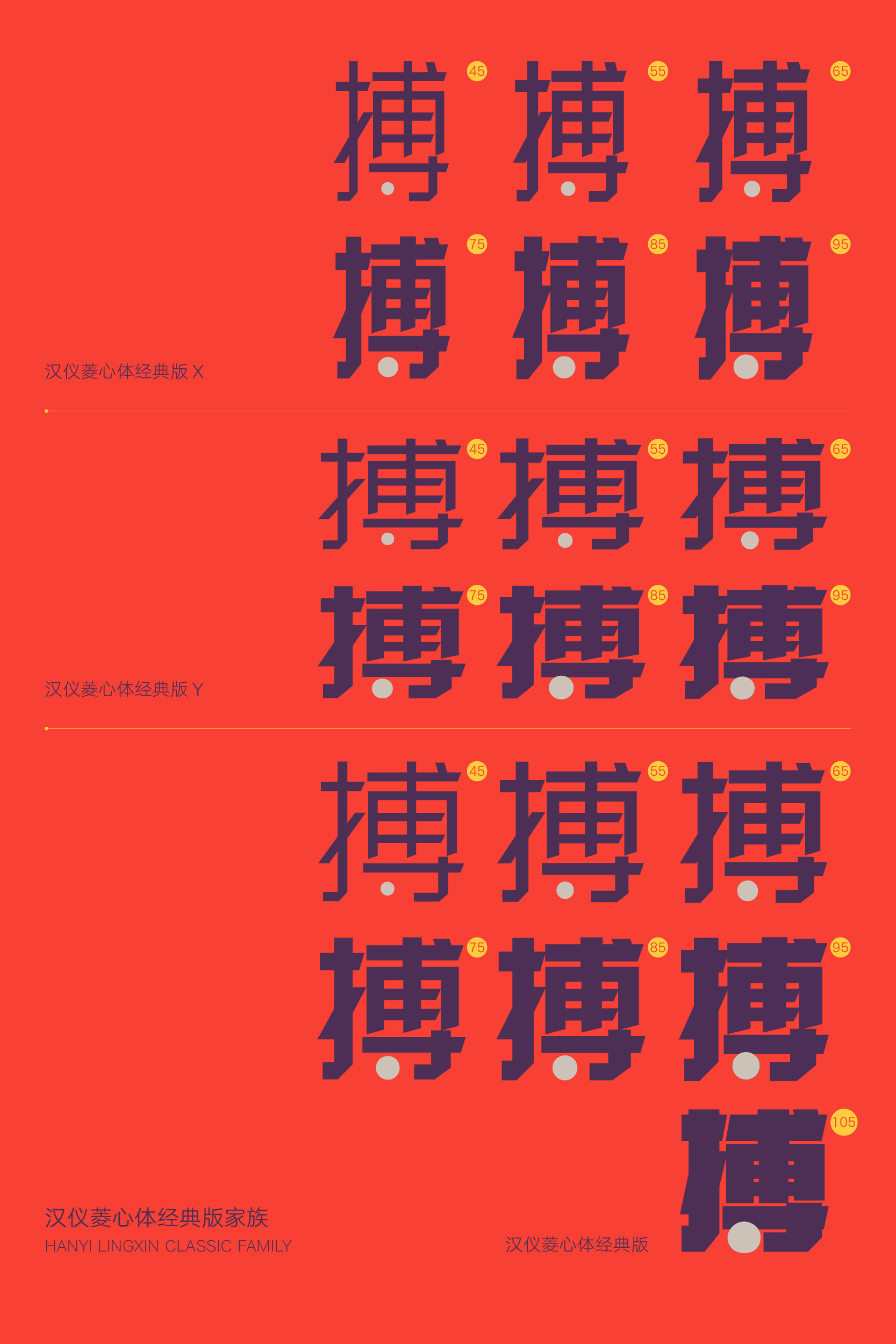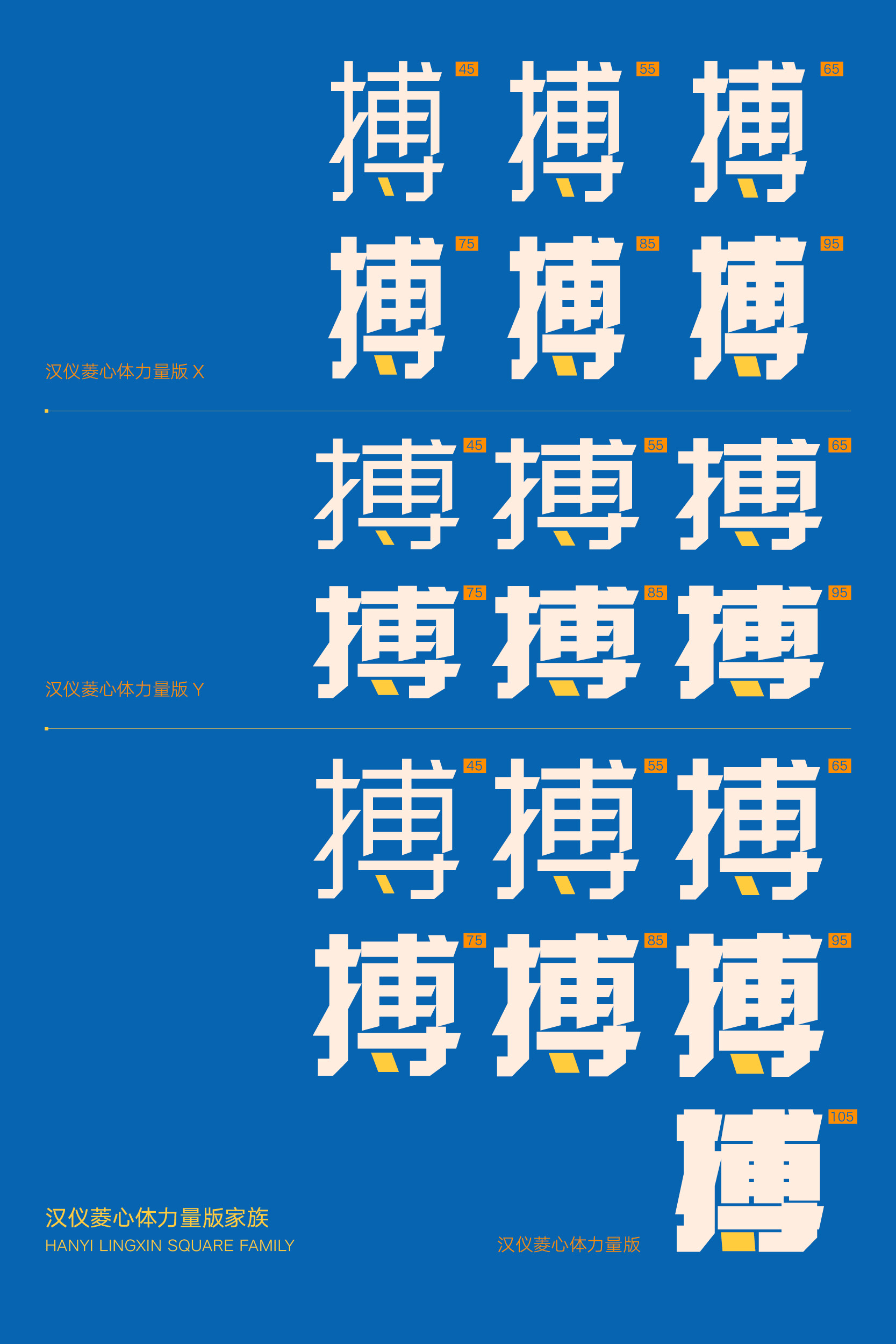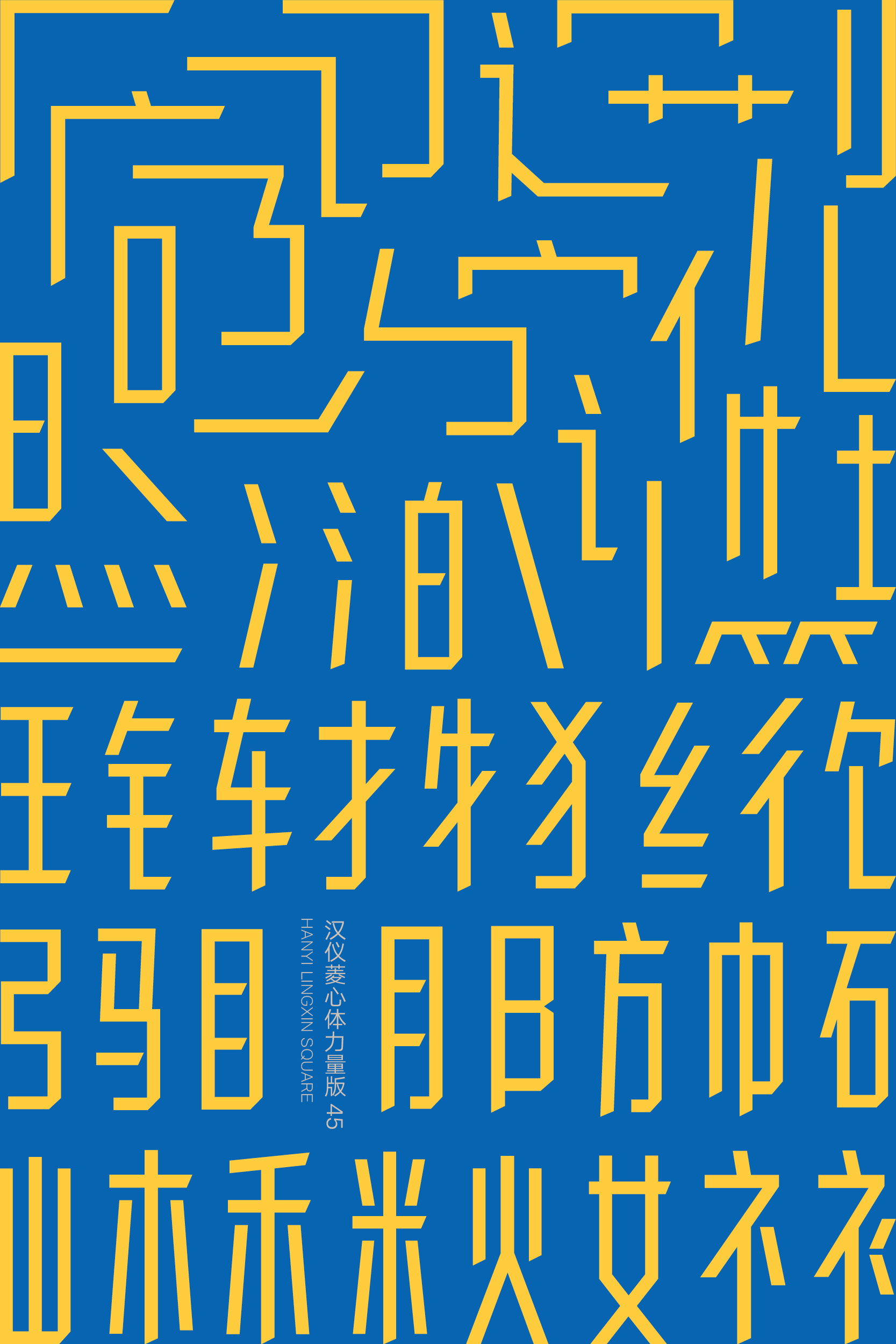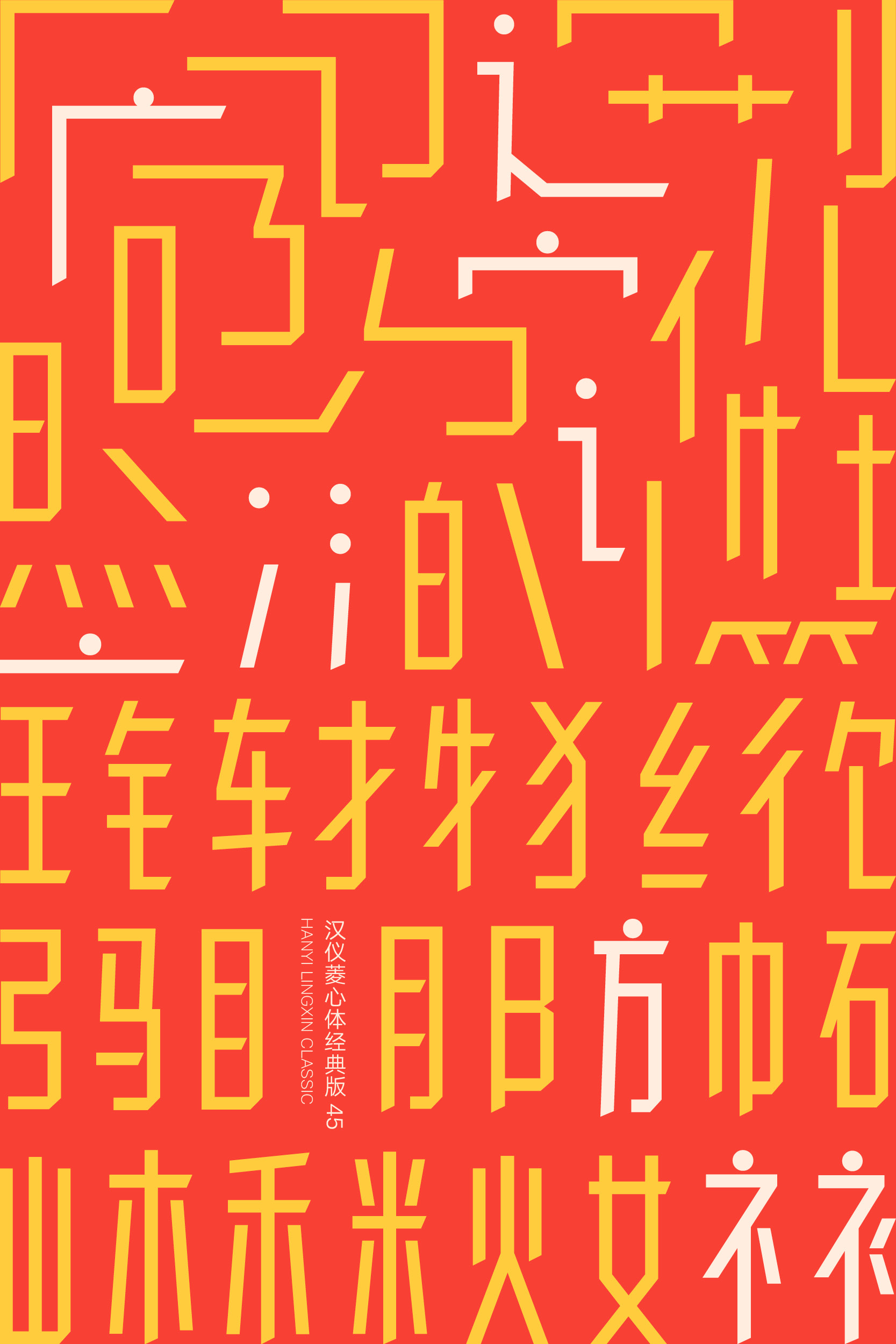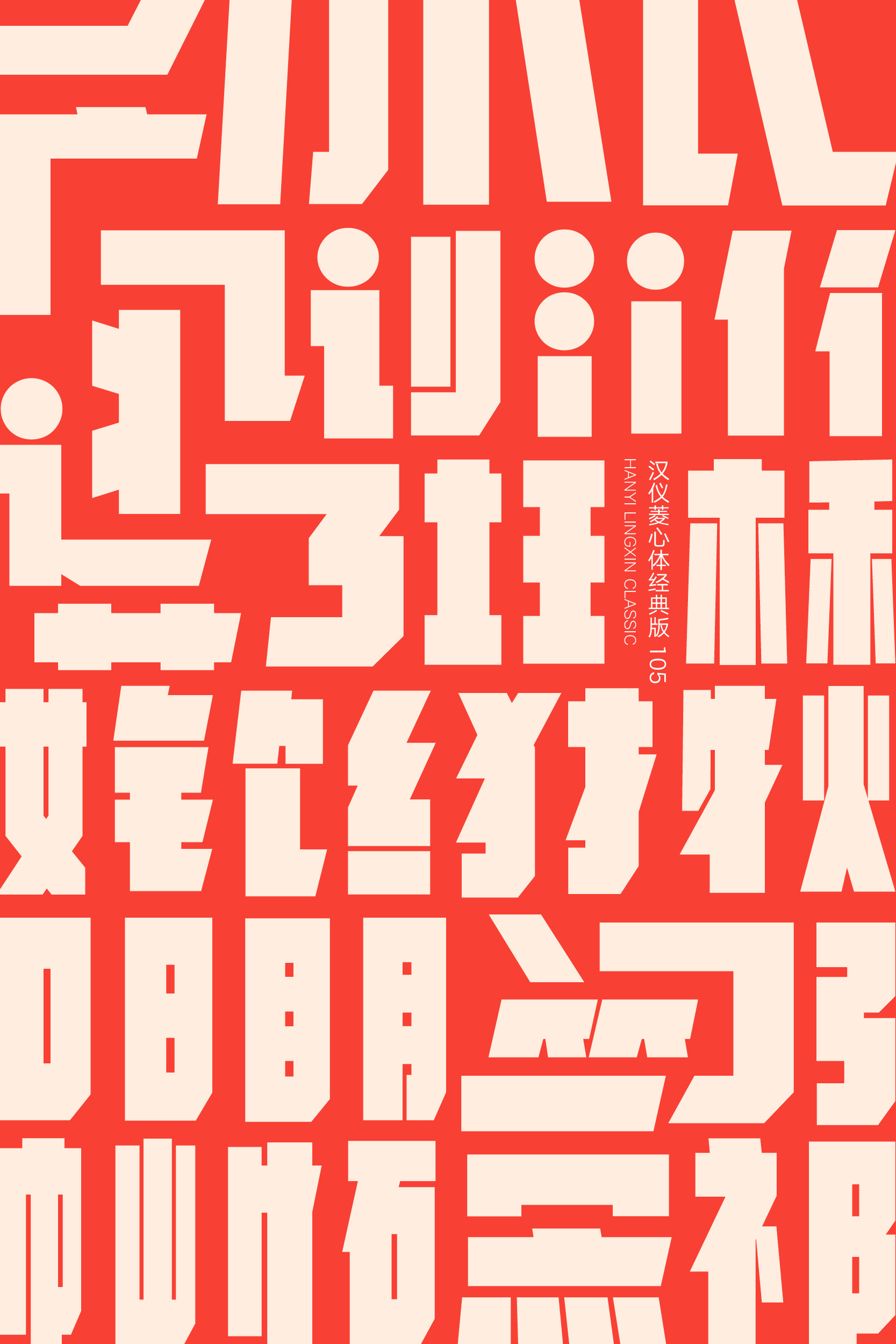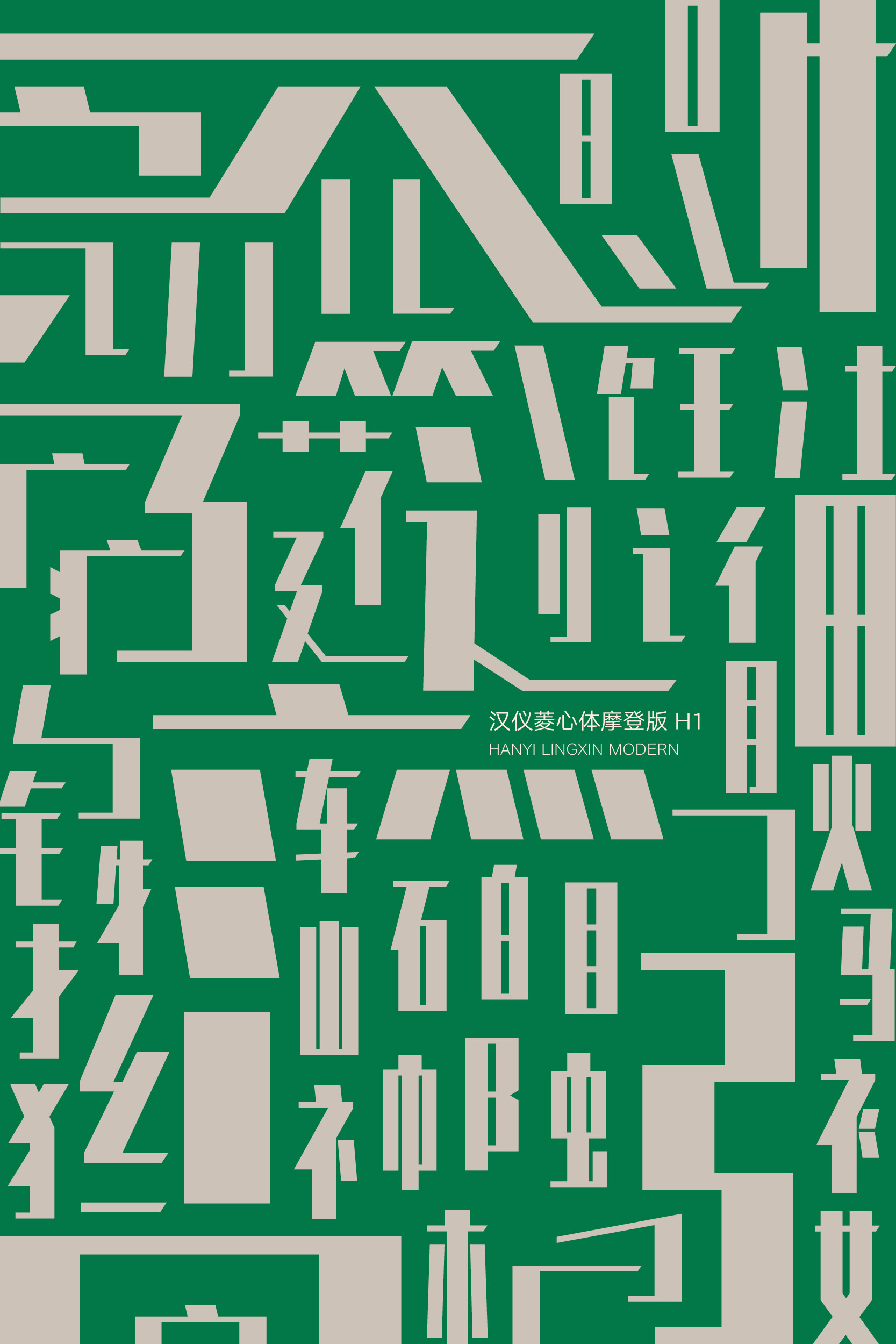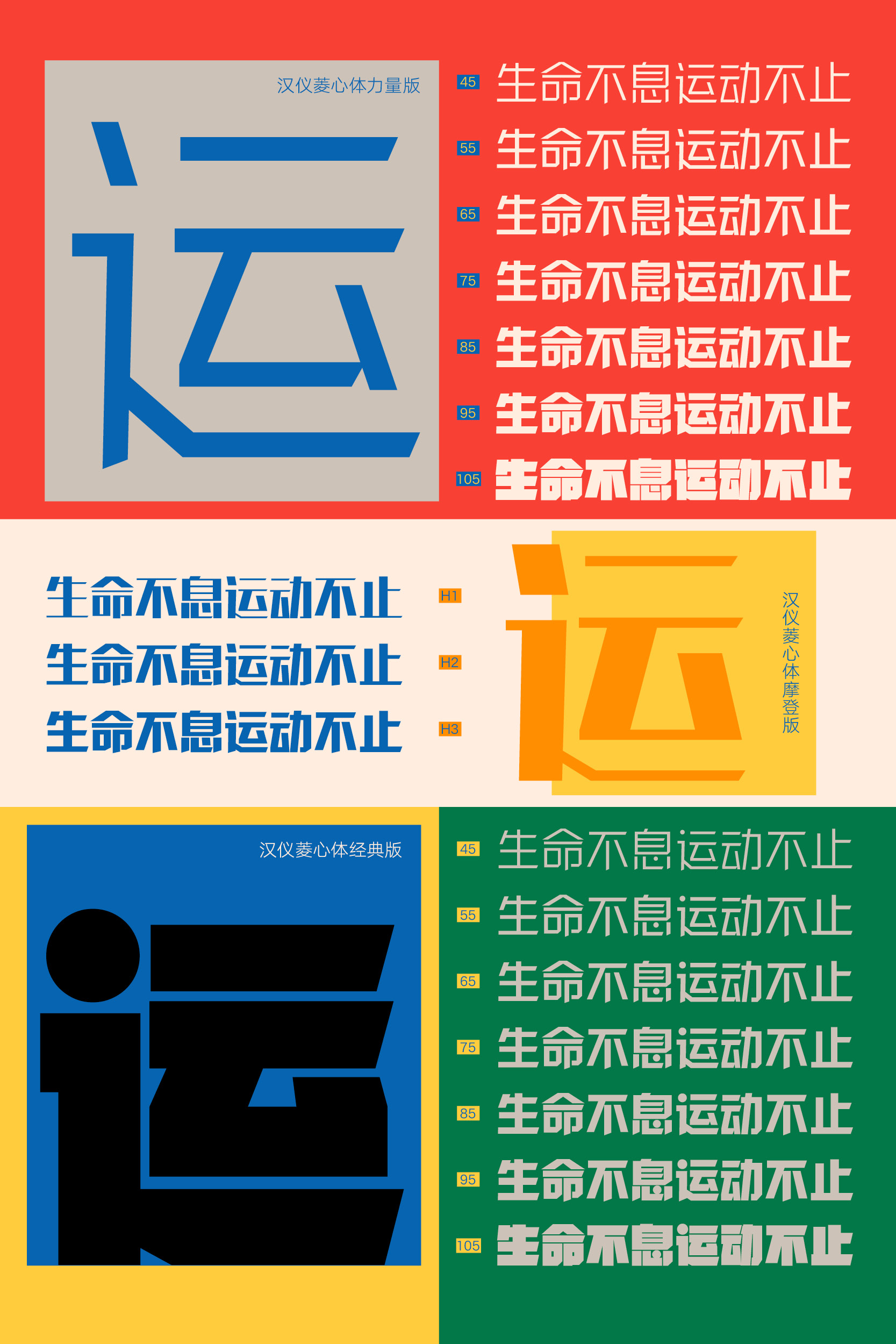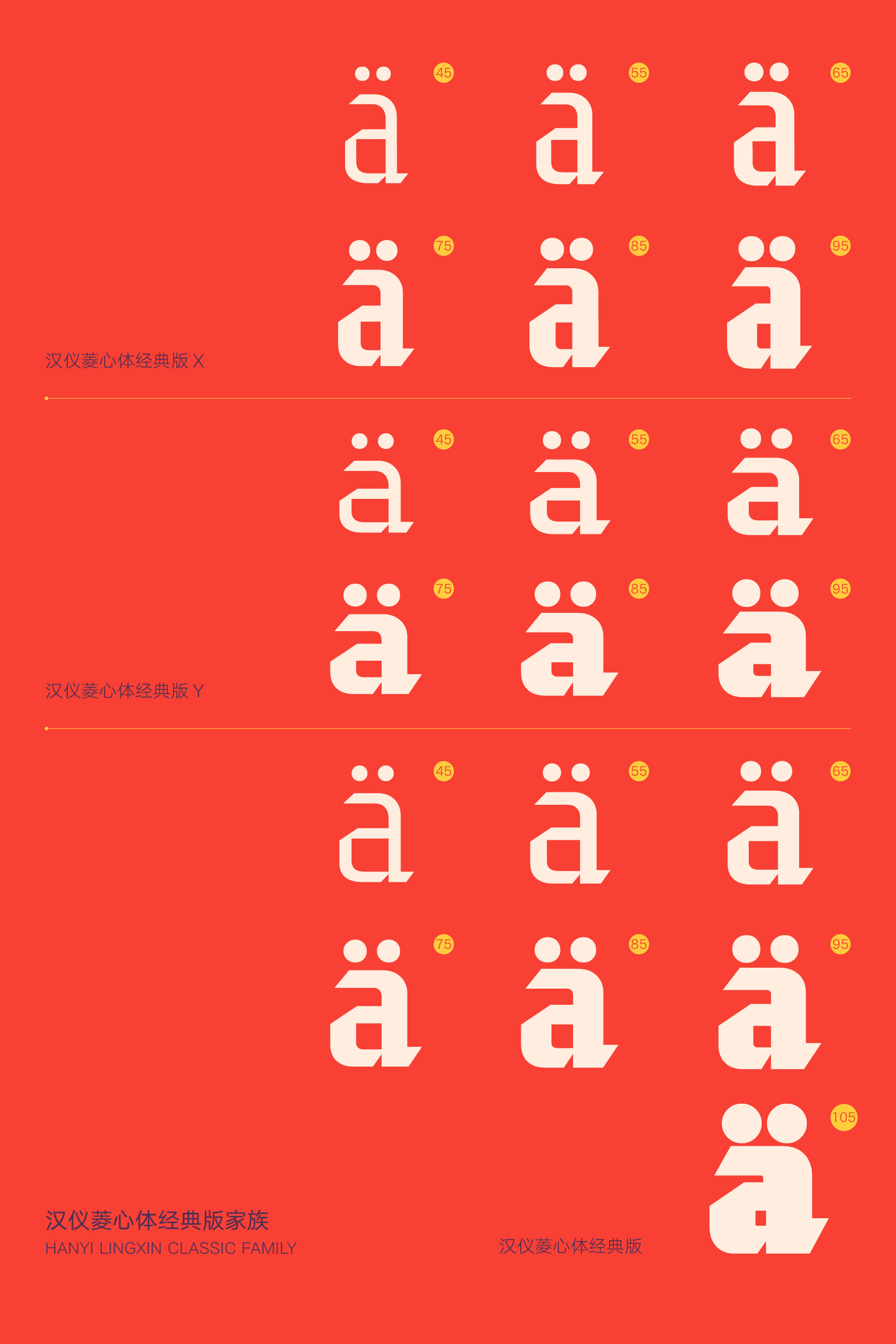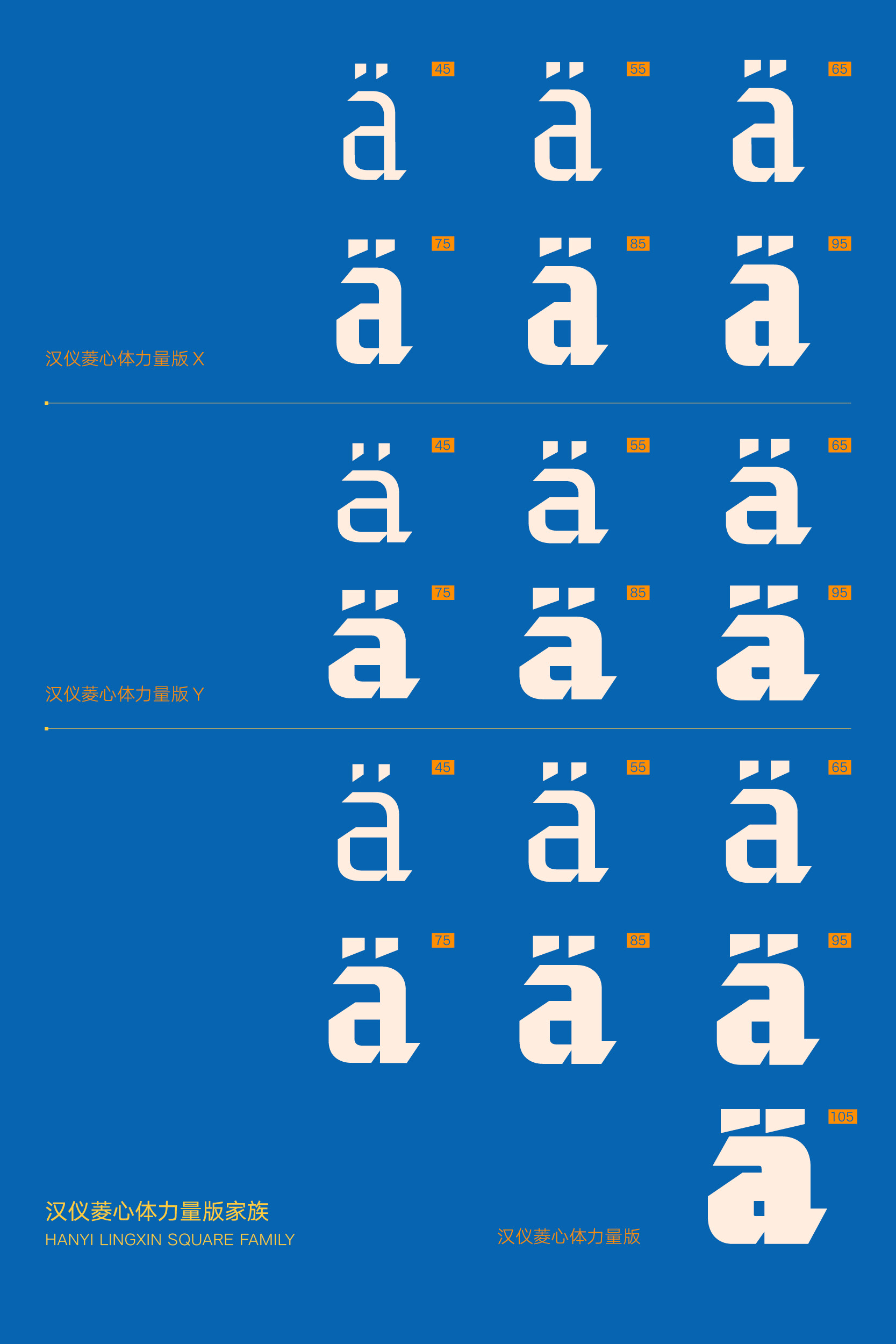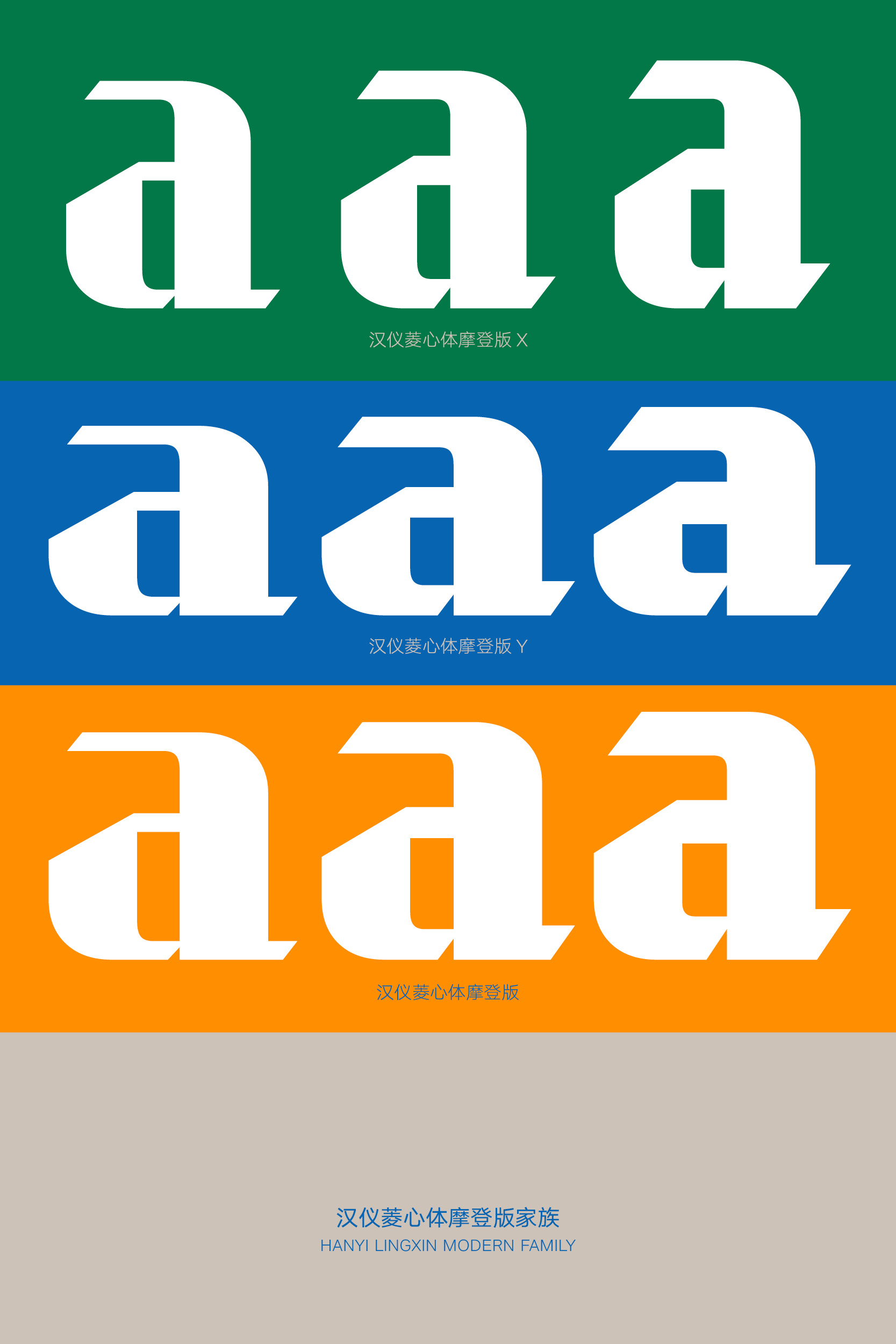
百变菱心,重塑经典
现代 / 几何 / 经典 / 力量 / 摩登
汉仪菱心体最初发布于2000年,这款字体以其极具冲击力的块面感造型和标志性的圆点和切角设计在字体市场中长期占有一席之地,至今依然频繁出现在各式各样的广告、招牌和影视节目中。千禧年以来的二十年间,字库设计与技术支持不断发展进步,大众审美也不断发生变化,为了更好地适应今天的字体使用场景,汉仪菱心体通过可变字体的原理,得到全新的立体化家族设计,不仅优化了设计细节,而且从字重、笔画造型、字面比例多个维度升级为包含多达47款字体的超级字体家族。
全新的汉仪菱心家族分为经典版、力量版和摩登版三个各具特色的系列,由原来的单一字重扩展至最多七个字重,还对正体分别进行横向、纵向的变化拓展出X和Y两种不同的字面比例,共计47款字体。
汉仪菱心体经典版保留了原版菱心体标志性的圆点和切角,字形端正,笔画平直,并以此为基础进一步提升了字面美观度。
笔画由横细竖粗调整为视觉上横竖等粗,字面布白更加均匀舒适,尤其在较细的字体中呈现出整体性更佳的视觉效果。
原版全直线笔画和水平切角导致的字体虚尖问题,错位调整了笔画尖角的角度,让问题得到解决;对竖撇画的角度进行微调,和竖画区分开来。
汉仪菱心体力量版在经典版的基础上将圆点变为方点,这一笔形上的变化使之具有更强的块面感和冲击感,可以更精准地适应不同场景的使用需求。
汉仪菱心体经典版和汉仪菱心体力量版均已扩展至七个字重,在保留字形特征的前提下,达到了更丰富的视觉层级。
汉仪菱心体经典版和汉仪菱心体力量版的最大字重达到了105,将笔画做到极粗、块面感做到极强。相比于一般的85、95字重,105字重的菱心体字白被压缩至可识别的极限,不推荐用于小字号的排版,但是在大字号的标题环境中,它会为设计带来独特的视觉体验。
菱心体的105字重并非简单的字重变化,而是根据菱心体基本特征重新设计的一款极具重量感的超级黑字体。笔形依字形内部空间灵活变通,对一些部件进行合笔处理,使负空间整齐有序。笔画复杂的字形中着重加粗主笔或外侧笔画而减细副笔使之平衡。
汉仪菱心体摩登版则是延续了原版横细竖粗的笔画设计,并夸张粗细对比,试图达到一种轻量摩登的视觉语言。横笔画的粗细度有三种变化(H1、H2、H3)。
这款字体对比强烈的横细竖粗与简洁概括的直线笔画碰撞出了一丝民国时期美术字的味道,因此命名为“摩登”,兼具现代新潮和怀旧复古的气质。
对一款字体进行直接压扁或拉长的变形会破坏字体原本的结构、比例、布白,甚至影响可读性。那么,如果遇到“我想要这行字扁一点”或是“我想要这行字长一点”这类需求,该如何解决呢?汉仪菱心体探索了在字体X轴、Y轴变化的可能性,得到了字形瘦长的X和字形扁宽的Y,为特定的使用场景交上一份满分答卷。
汉仪菱心体的西文设计延续了中文设计的块面感,方直有力,结合西文字形巧妙地加入直线笔画切角的设计细节,并保留部分弧形笔画以保证可识别性。
汉仪菱心体经典版、力量版、摩登版的西文设计与中文设计语言一致,在标点符号中也有所体现,搭配使用和谐统一。